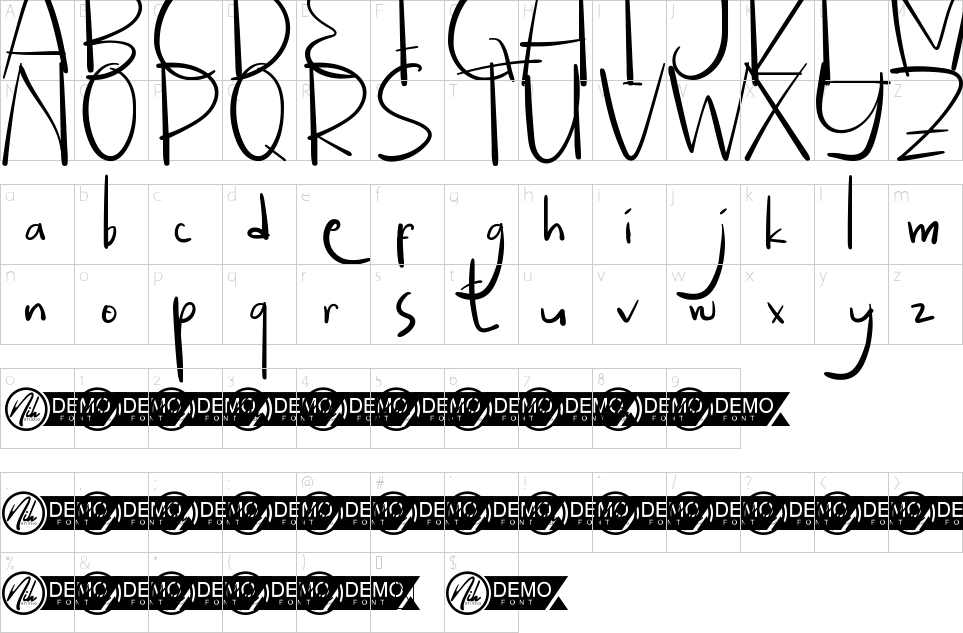
Aqui está uma descrição em português para a página de download da fonte ‘Menanti Hujan Font’: Descubra ‘Menanti Hujan Font’, uma fonte elegante e minimalista disponível gratuitamente para Windows e Mac. Desenvolvida pelo estúdio NihStudio, essa fonte se destaca pelo seu equilíbrio perfeito entre leveza e força, tornando-a uma escolha ideal para ambientes digitais que valorizam um design limpo e sofisticado. Não é à toa que essa fonte já foi baixada 272 vezes, revelando seu valor e popularidade entre designers e criadores de conteúdo. Se você busca uma fonte que combine facilidade de uso com um design impecável, ‘Menanti Hujan Font’ é uma fonte que não pode faltar em seu arsenal de ferramentas de design. Baixe agora e explore todos os seus recursos.